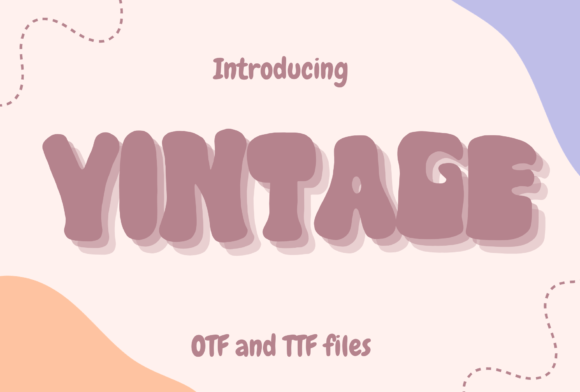
Vintage
Ulasan Lengkap Font Vintage – Sentuhan Klasik untuk Semua Proyek Anda
Jika Anda sedang mencari font vintage yang memadukan keanggunan retro dengan kepraktisan modern, maka koleksi Vintage fonts ini adalah pilihan yang tepat. Dirancang dengan gaya tulisan tangan yang super cute, font ini menawarkan tampilan sederhana namun tetap menarik untuk berbagai keperluan, mulai dari edukasi hingga iklan.
Fitur Utama yang Membuat Font Vintage Menonjol
- Desain Handwriting yang Lucu: Garis-garis halus dan lekukan alami menciptakan nuansa ramah dan bersahabat.
- Sederhana & Mudah Dibaca: Cocok untuk materi pengajaran, presentasi, dan materi edukatif lainnya.
- Serbaguna: Ideal untuk iklan, ilustrasi, desain grafis, serta proyek kreatif multi‑purpose.
Kenapa Vintage Font Cocok untuk Pendidikan?
Guru dan dosen seringkali membutuhkan tipe huruf yang clear namun tetap menarik perhatian siswa. Vintage menawarkan:
- Kejelasan tinggi pada ukuran kecil, memudahkan pembacaan materi.
- Sentuhan kreatif yang dapat meningkatkan motivasi belajar.
- Kemampuan menyesuaikan warna dan efek tanpa kehilangan kualitas.
Penggunaan dalam Iklan & Ilustrasi
Dalam dunia pemasaran, keunikan visual menjadi kunci. Font Vintage menambah:
- Karakter retro yang menonjol di antara iklan konvensional.
- Konsistensi branding untuk produk yang mengusung tema nostalgic.
- Kemudahan integrasi dengan elemen grafis modern.
Kesimpulan – Pilihan Tepat untuk Semua Kebutuhan Desain